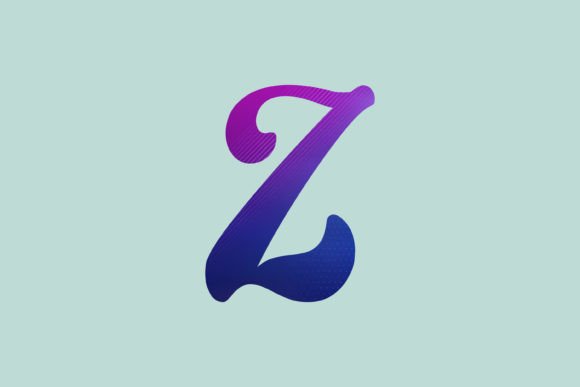
Gradient Sublimation Font Z
適切なデザイン要素を見つけるのは難しい場合がありますが、Gradient Sublimation Font Zは作品を即座に引き立てる優れたコレクションを提供します。
POD(オンデマンド印刷)製品、結婚式の招待状、またはソーシャルメディアのグラフィックを作成している場合でも、Gradient Sublimation Font Zは理想的です。